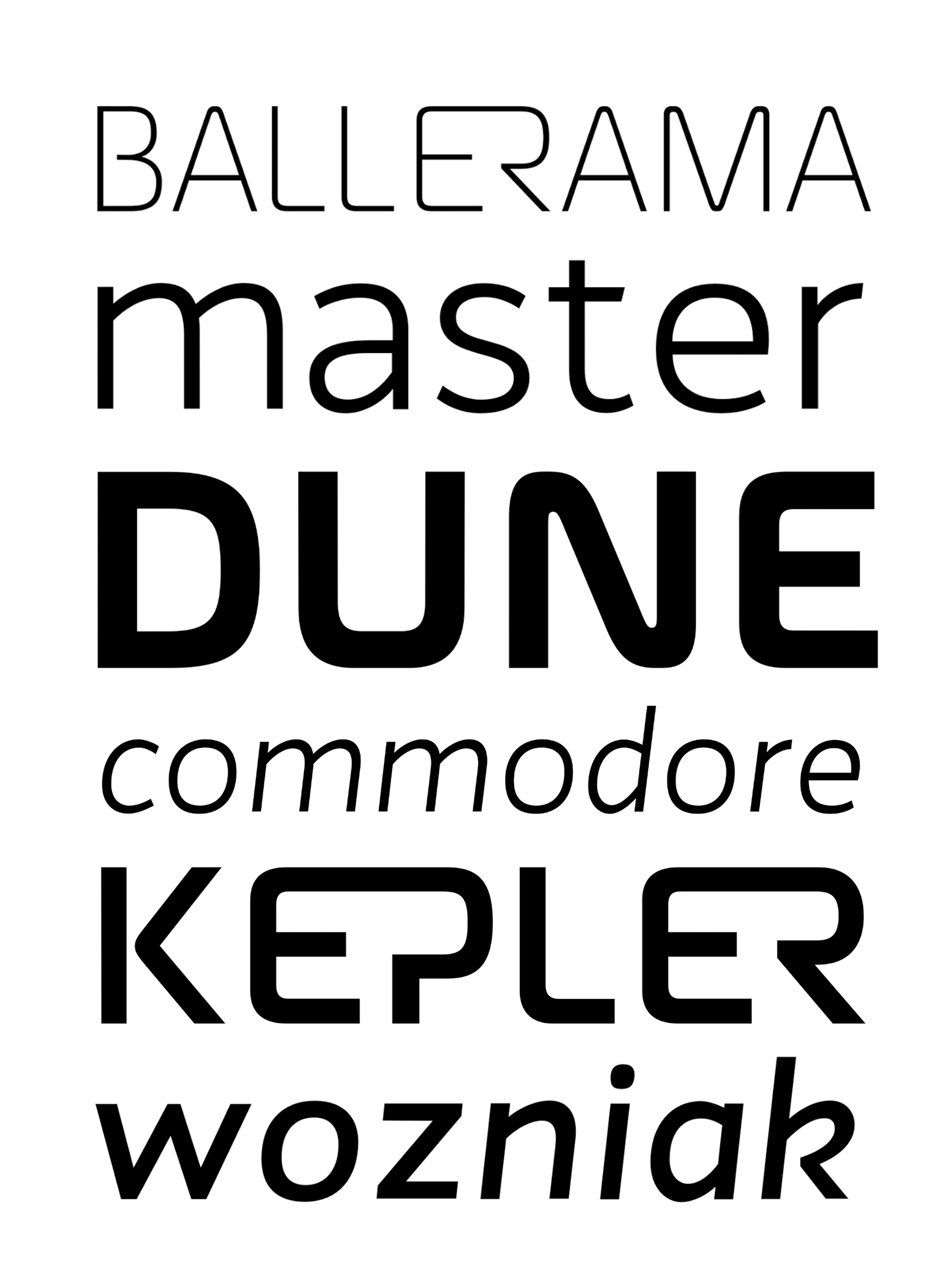
| Descripción | Wozniak es un tipo de letra sanserif en 16 estilos que incluye una fuente para pantalla de 16 estilos en sí misma. En sus formas predeterminadas aporta una personalidad moderna, clara y brillante al texto y una amplia gama de posibilidades al admitir muchas características OpenType, como números oldstyle, de línea y tabulares, versalitas, inferiores y superiores, ligaduras discrecionales, numeradores y denominadores, fracciones extendidas, formas sensibles a mayúsculas y minúsculas y mucho más, todo ello cuidadosamente elaborado y equilibrado para una excelente legibilidad y un rendimiento óptimo tanto en pantalla como en papel. Pero eso no es todo, cada estilo incluye también dos juegos completos de mayúsculas alternativas y más de 180 ligaduras estilísticas inspiradas en la revolución digital y la estética de principios de los 80. Todo ello se funde en un conjunto flexible y multifuncional de más de 1.600 glifos, compatible con más de 200 idiomas de escritura latina y con la posibilidad de utilizarlo en configuraciones de texto largo, titulares o marcas, pasando de lo moderno a lo vintage con absoluta facilidad y naturalidad. Wozniak lleva el nombre de Steve Wozniak como homenaje a los pioneros de la revolución digital. |
| Clasificación | Texto |